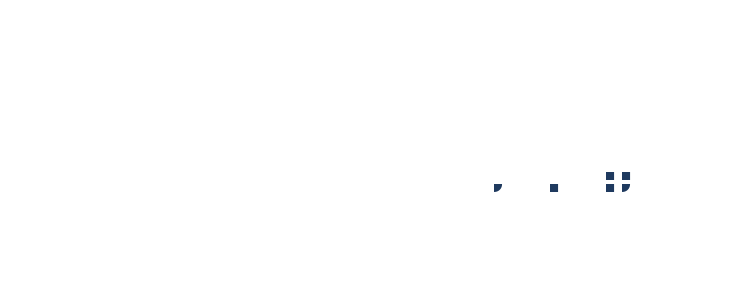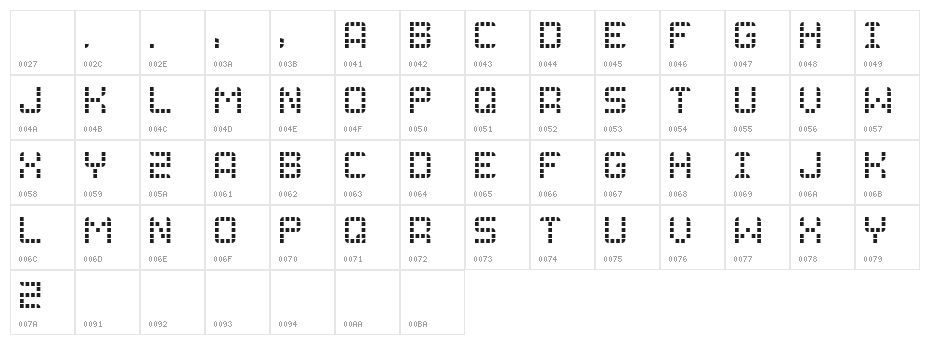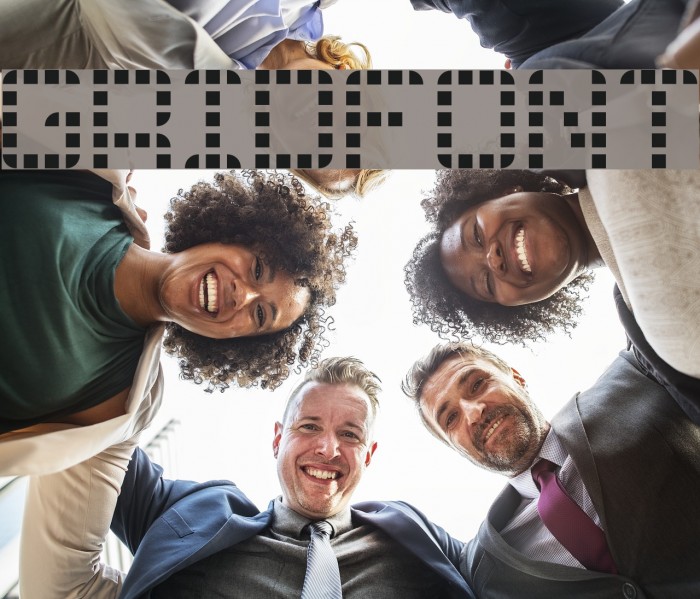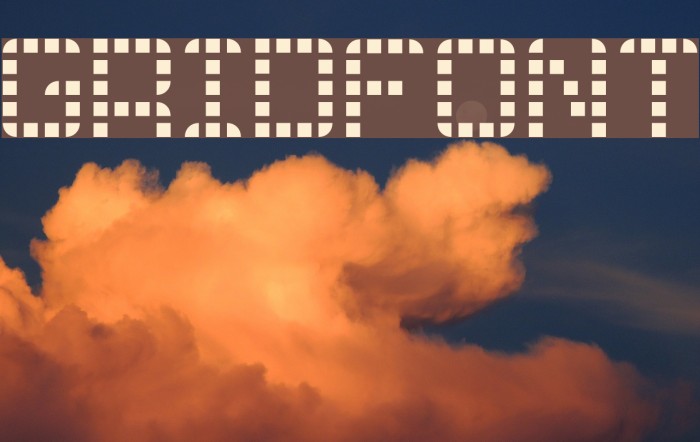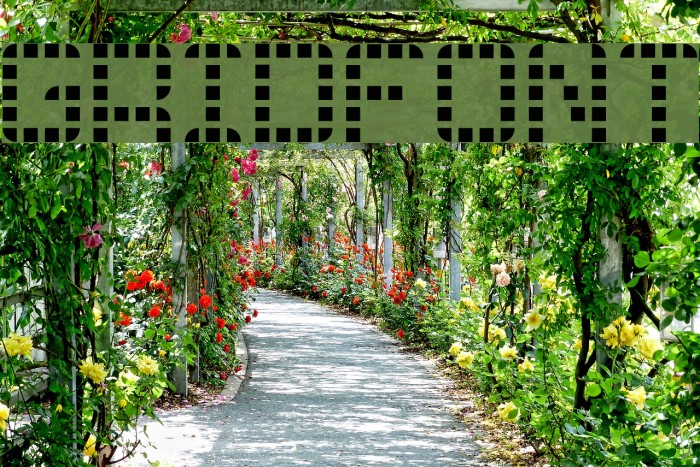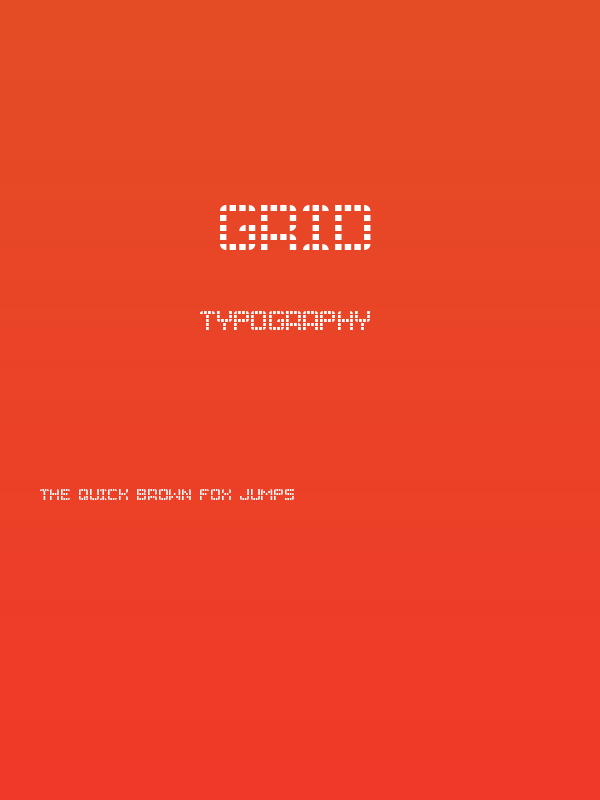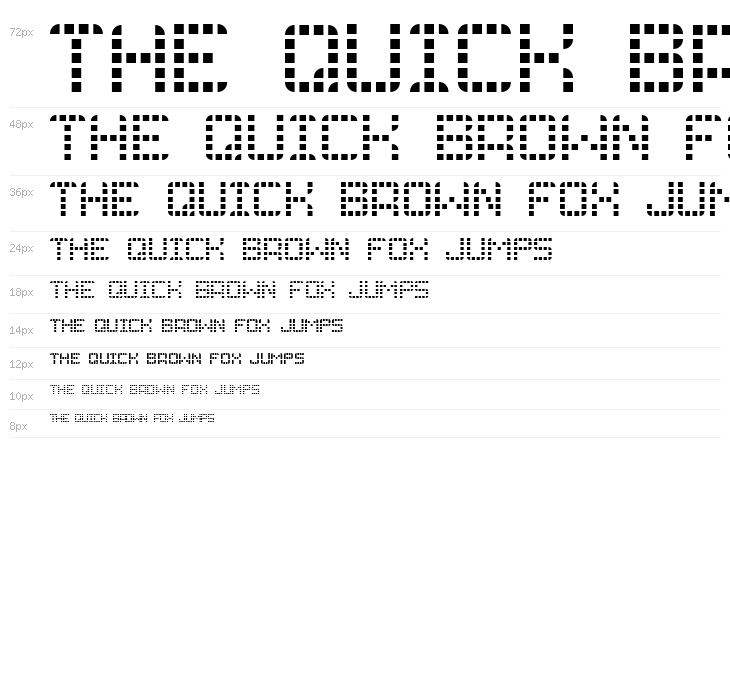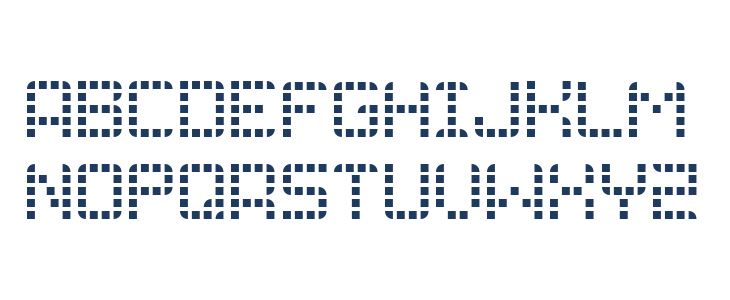
Grid Font
| Kategorien | Futuristic |
| Anwendungsfall | Headlines, Logos, Digital Interfaces |
| Vorgeschlagene Projekte | Ideal for digital interfaces, tech-themed designs, video game graphics, and modern art projects. |